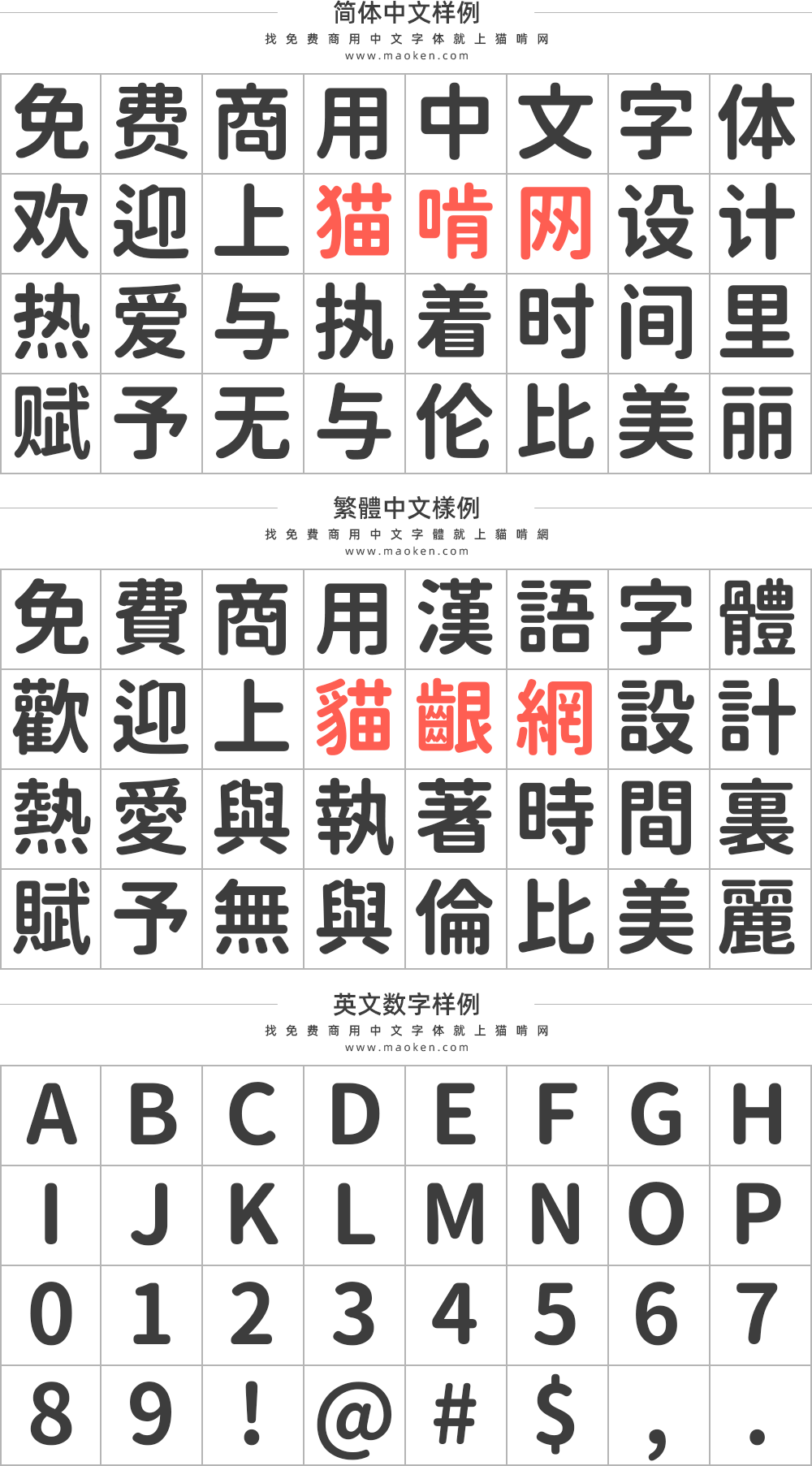
| 字体作者:But Ko (中国台湾) | 字体字重:7个 |
现在可以免费商用的黑体字形非常多,例如思源黑体, 阿里巴巴普惠体 ,还有最近OPPO发布的OPPO Sans 品牌字体等等,但是非常可惜的是可以免费商用的圆体却是非常少。我所知的就是源柔黑体,Rounded Mgen+这些是圆体,但是它们都是日本设计师基于M+字体开发的,字符集采用的是日本的JIS标准,所以对简体的支持并不是十分的好。
而且像源柔黑体之类的字体都留有黑体的脚,乍看的感觉还是很黑体。 而源泉圆体不只把笔画全改圆,也将黑体的脚尽可能拔除,并加上封闭区域的内圆角处理,尽可能去逼近圆体样貌。
源泉圆体是基于思源黑体的开放原始码中文字体,通过电脑程序自动进行改造而成的字体,所以无论是字符集和字重都是跟 思源黑体一样。这意味着对简体中文的支持也十分良好,基本上不会存在缺字的问题,这个十分重要。但是由于是程序自动生成的字体,所以有些字可能会存在某些笔划的错误,请大家在正式使用时检查清楚。
本站有爱圆体和资源圆体推荐过来的,这是思源柔黑去拔脚的吧和资源圆体没系。很多错别字随便举例“包画角直巩真亥八具所才与虎拔令外” 别说台湾写法了放到简体字就是错别字。一个部首错了就全错感觉错了1/5了
源泉黑体本来就是给台湾用户改造制作的字体呀~上面列举的写法多数属于旧字形范围(除了“包”可能是你用到了日文JP版;台湾版下面是巳不是己,跟规范字一样;“所”也一样左边用“戶”,JP则是“戸”)。如果真的觉得必要使用可以自行改造使用呢~
改造不如直接改造思源柔黑,比这个好看。字体太多了改不完的。直接用资源黑体就行了,这个不推荐用。不合符简体字的就是错别字,还特多。我知道他是给台湾用户改造的啊,但是描述有问题,Google的思源黑体包括很多字形,这个只是单独改造了tw那一种,对简体中文是不支持的。从思源柔黑和有爱圆体推荐这个就更离谱。思源柔黑才是思源黑体直接改造的,对各种中文都支持。
大陆的用户建议用江城圆体,是基于思源黑体SC改的
源泉圆体走字底有两个点,在国内用等于是错别字呀,我个人还是推荐资源圆体
两款圆体各有优缺点吧,源泉圆体毕是台湾的写法,而资源圆体没有拔脚,更像黑体。两款一起用会比较好
唯一不足的,简体的走字底边旁都是两个点
这应该是基于台湾版的思源黑体改造的,所以有些字不太符合我们简体的写法。
是韩国版吧